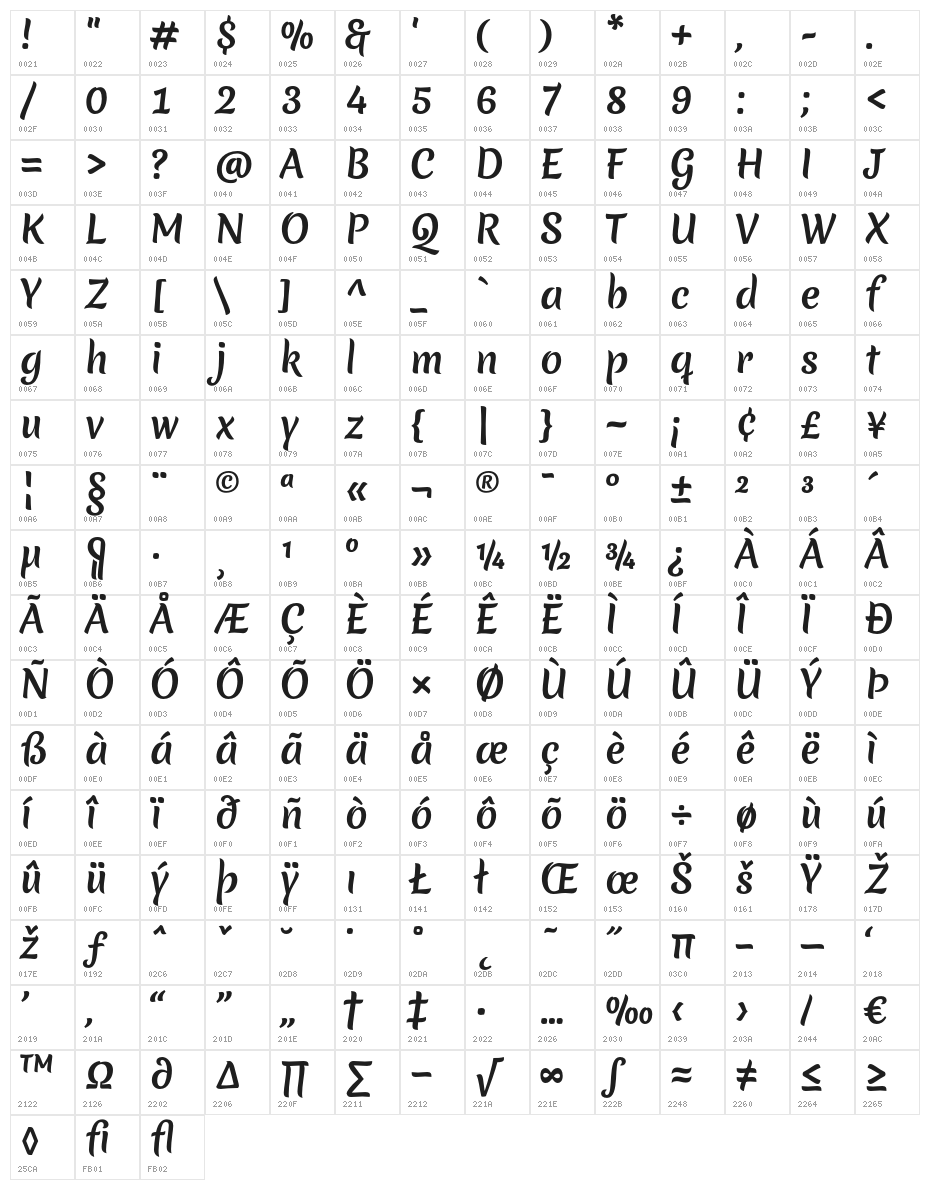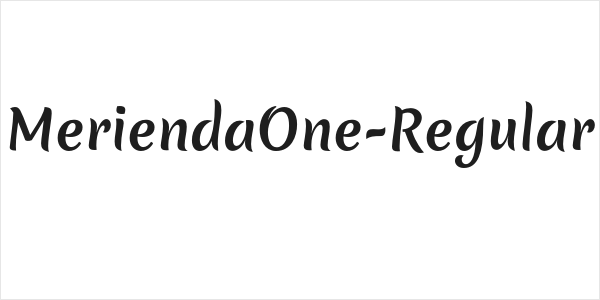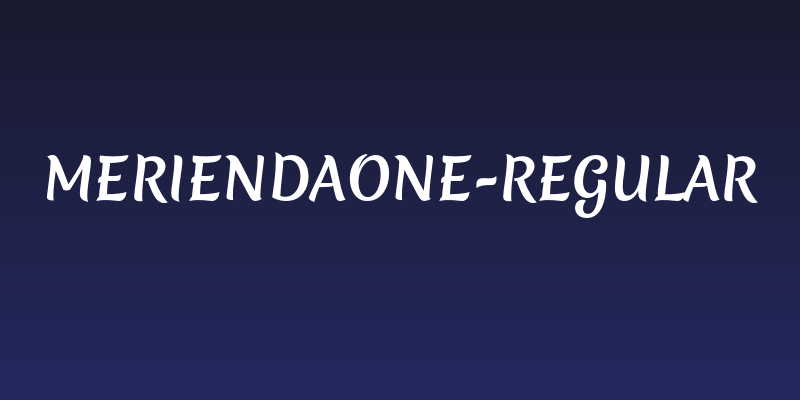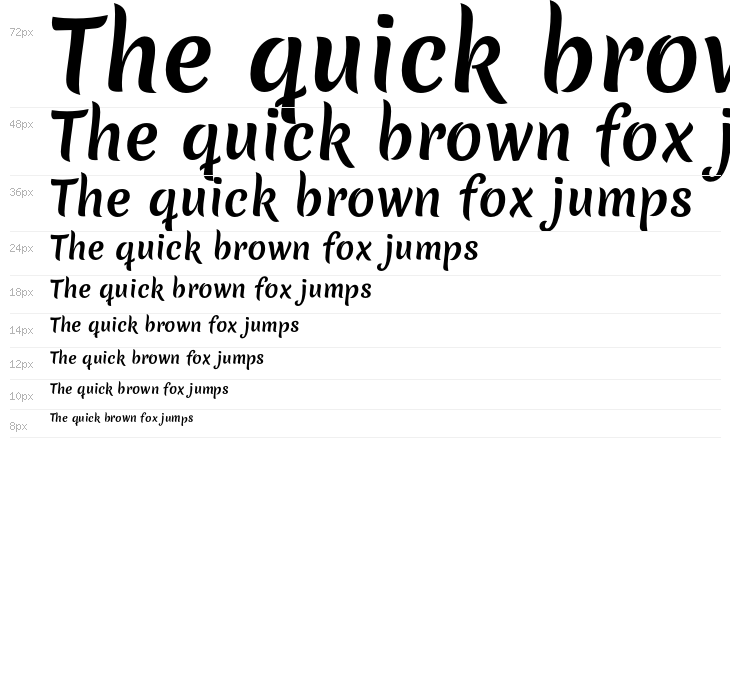
MeriendaOne-Regular Font
| Estilo general | Casual, Playful |
| Caso de uso | Headlines, Logos, Invitations |
| Proyectos propuestos | Ideal for invitations, greeting cards, playful branding, and informal designs. |